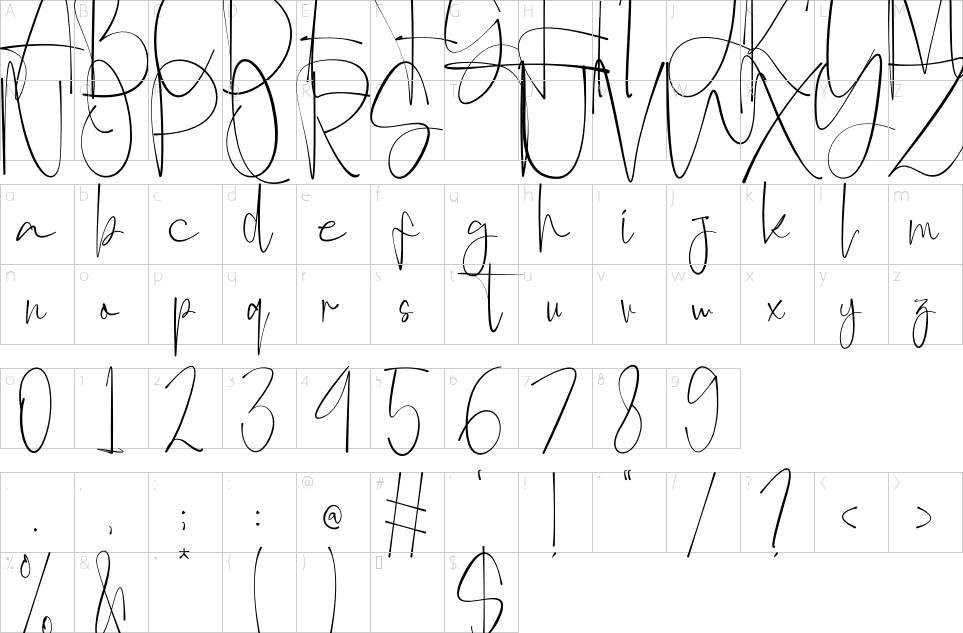
Anjany Sallentiny é uma fonte elegante e moderna, perfeita para aprimorar qualquer projeto gráfico. Lançada pelo designer desconhecido StringLabs, essa fonte é uma ótima escolha para aqueles buscando uma solução moderna e versátil para textos em seus projetos digitais. Com um design minimalista, a Anjany Sallentiny traz sofisticação para qualquer layout, seja para aplicativos, websites ou redes sociais. Essa fonte foi baixada 2.805 vezes, o que mostra a sua popularidade entre designers e profissionais de design. Se você está em busca de uma fonte de alta qualidade sem ter que pagar nada, Anjany Sallentiny pode ser sua escolha. Com um design limpo e fácil de ler, essa fonte é uma ótima opção para criar uma experiência de leitura agradável em seus projetos.